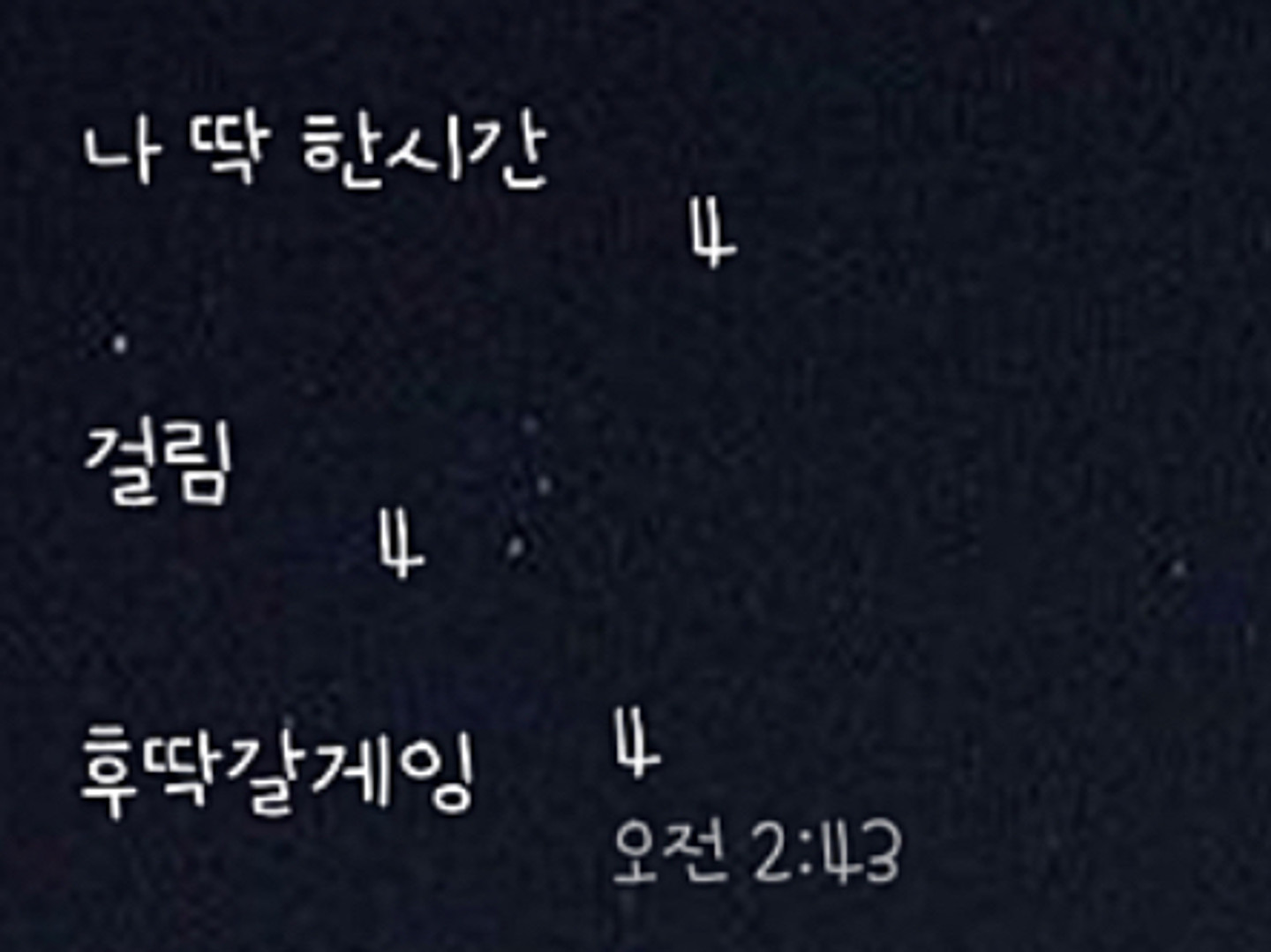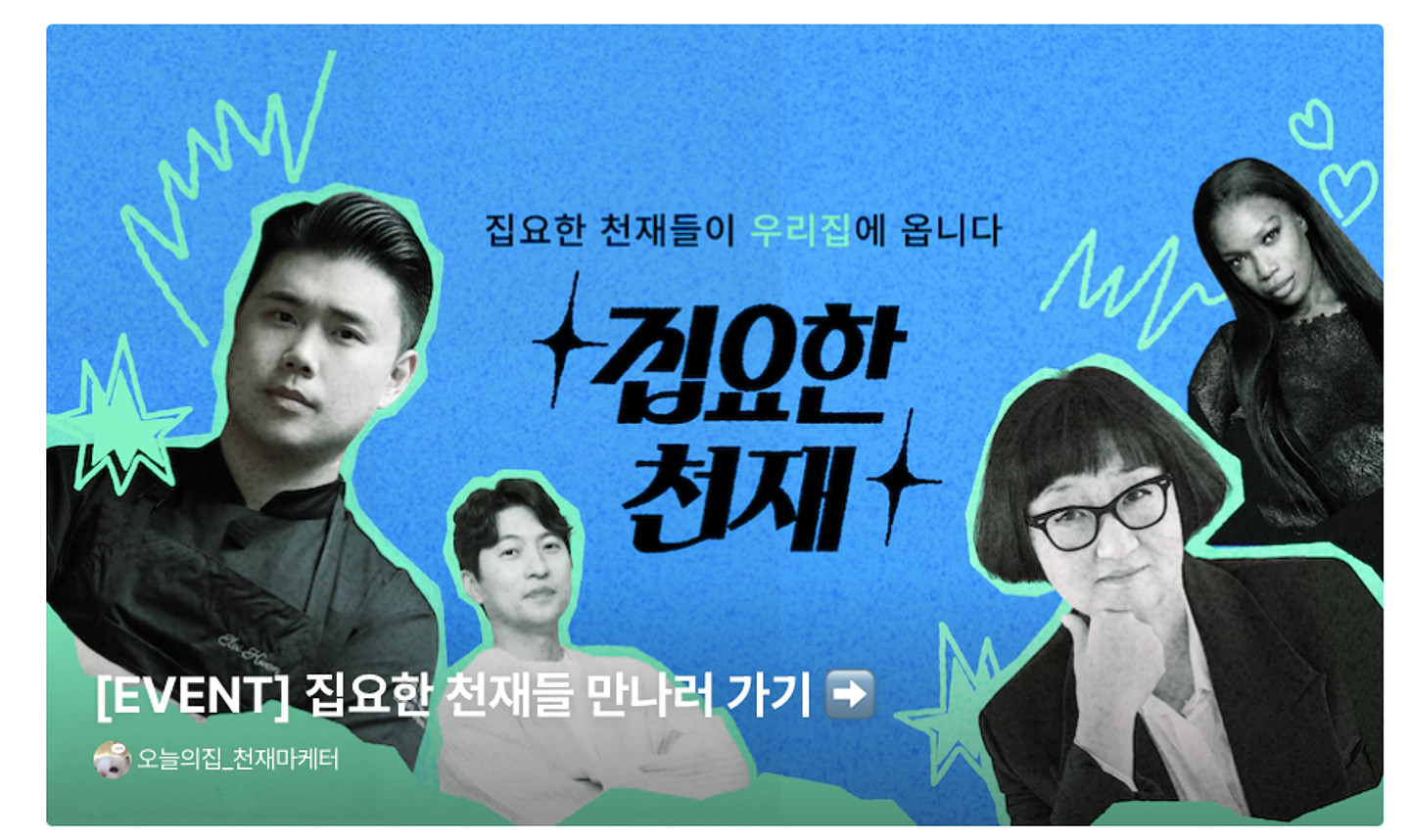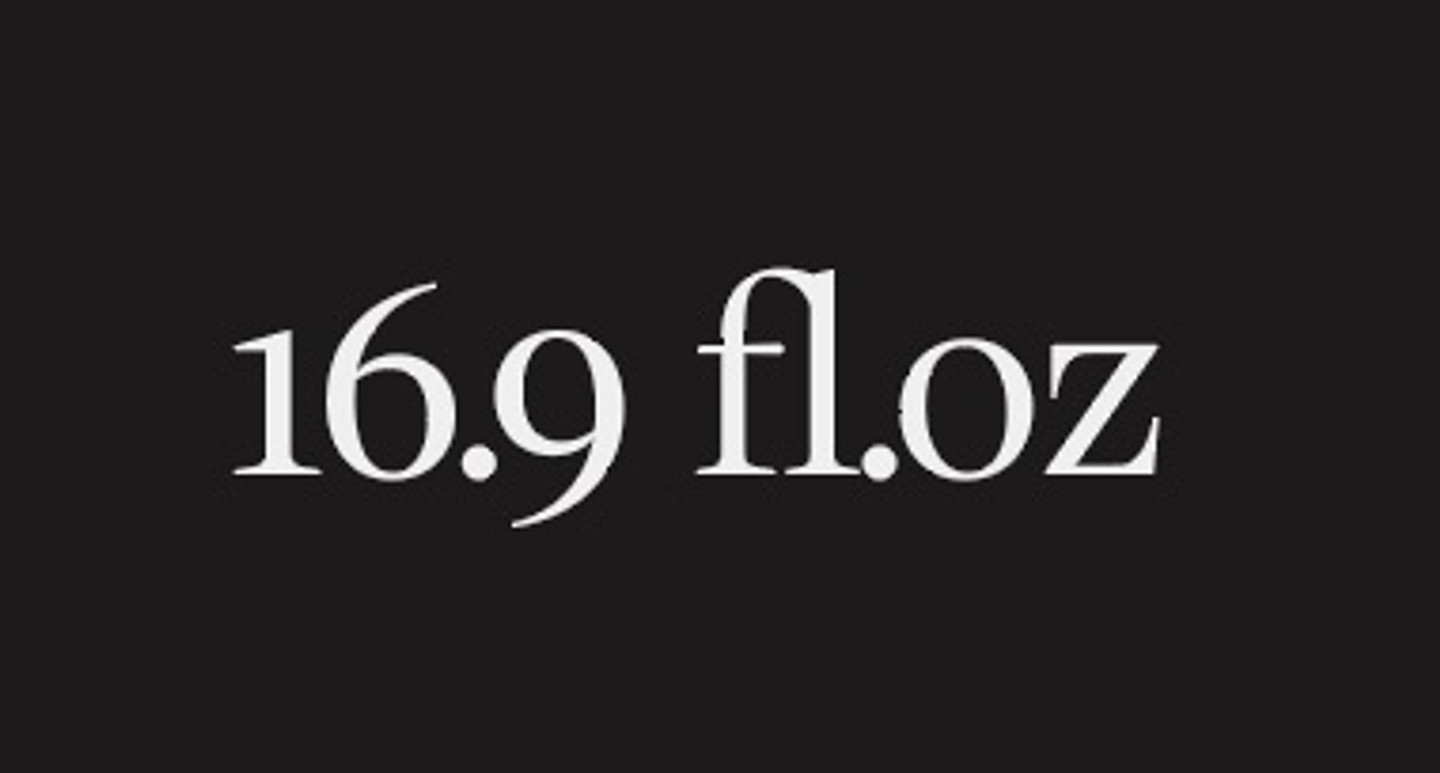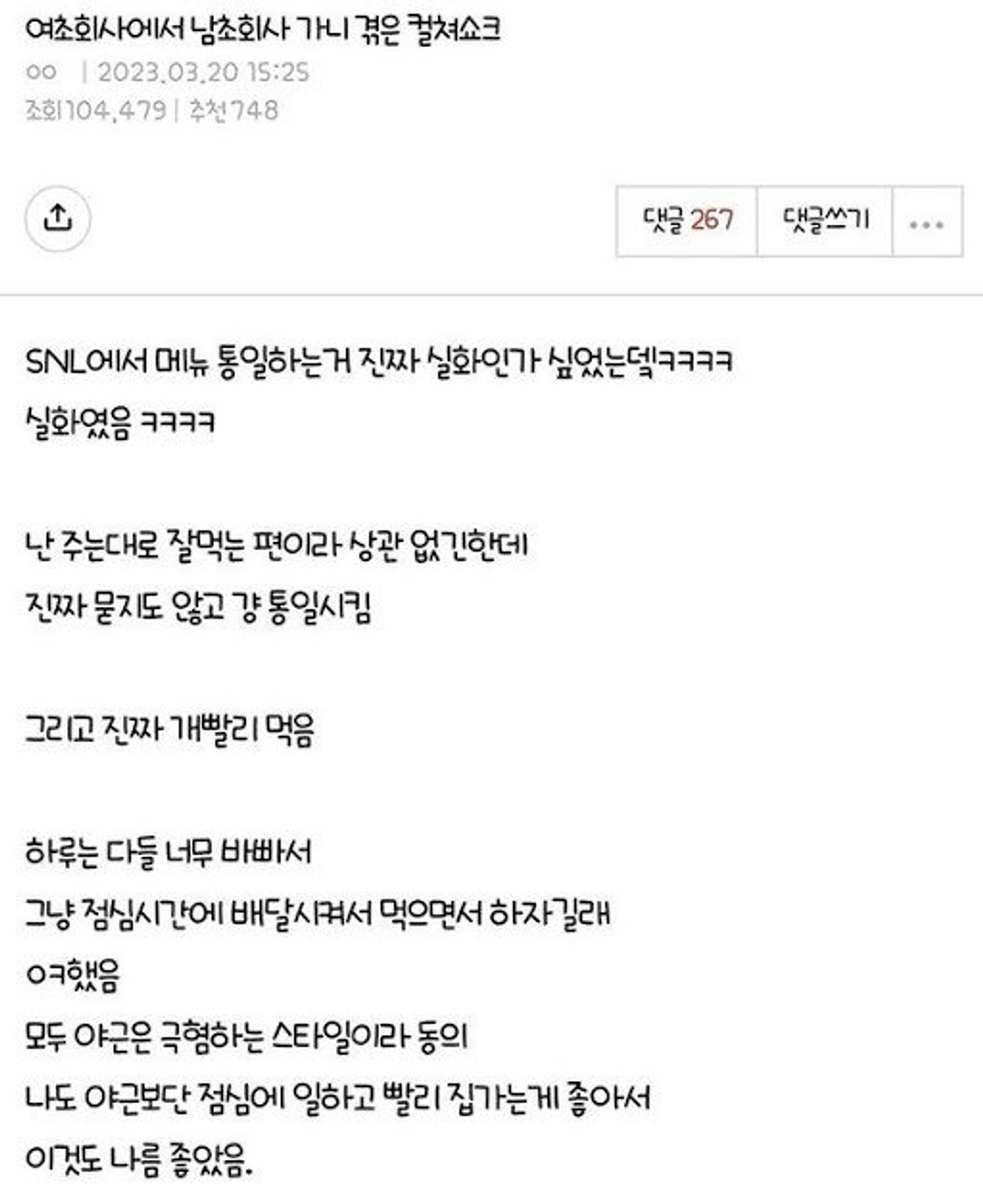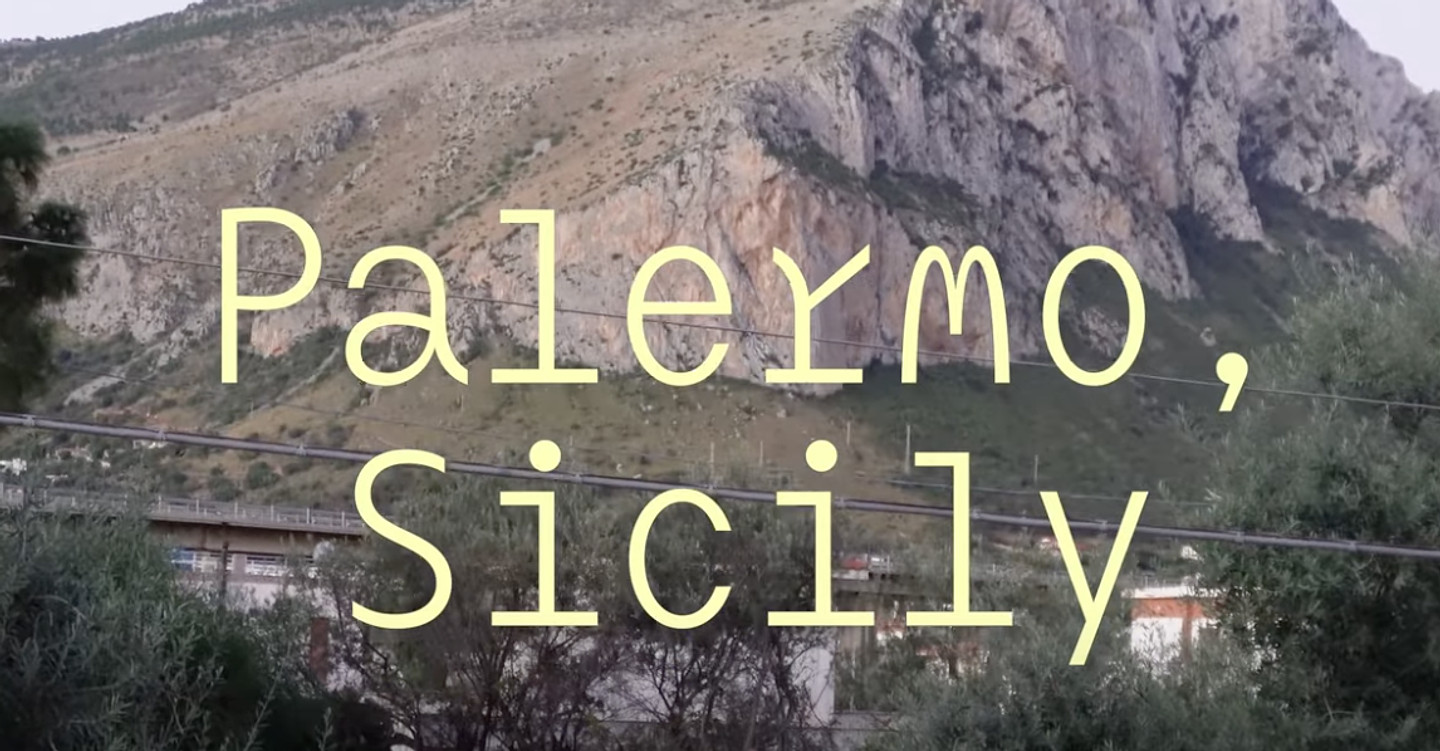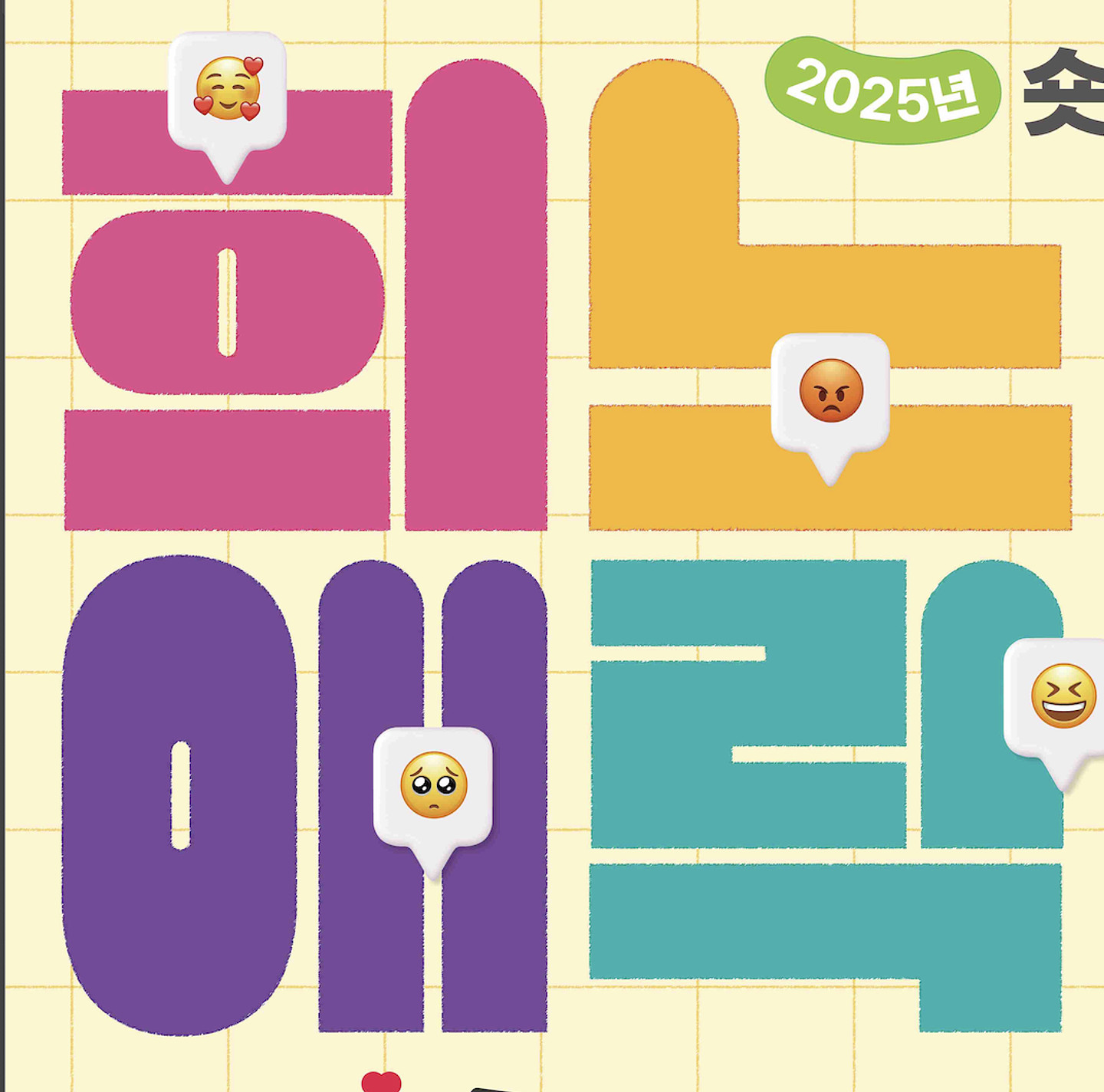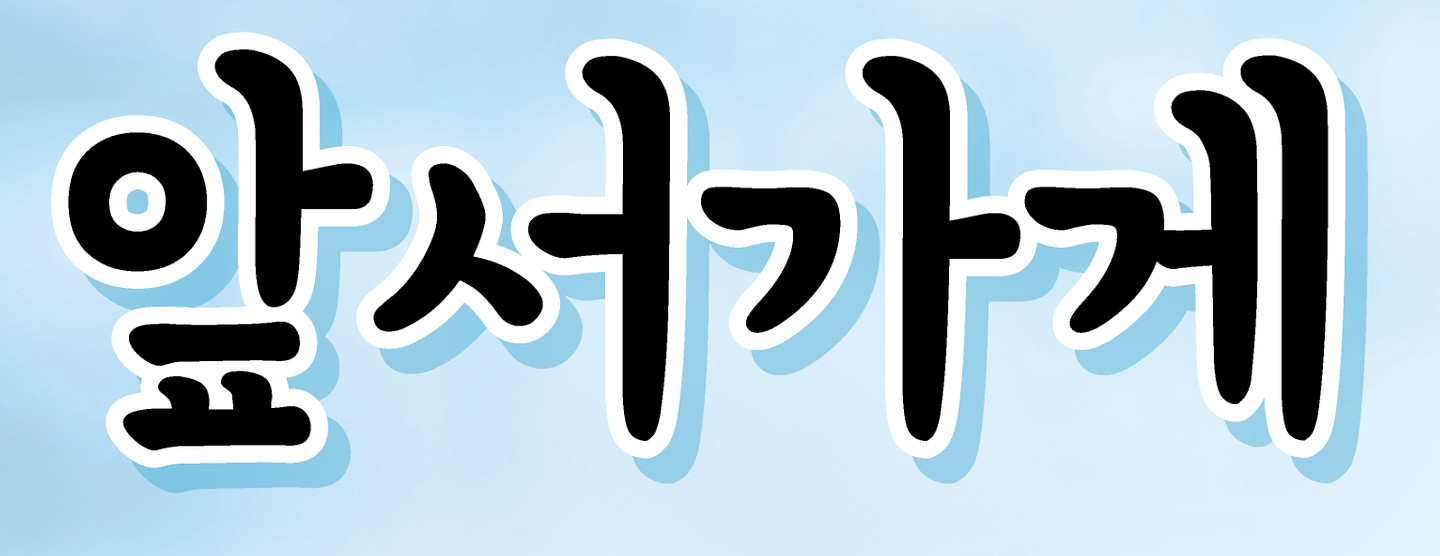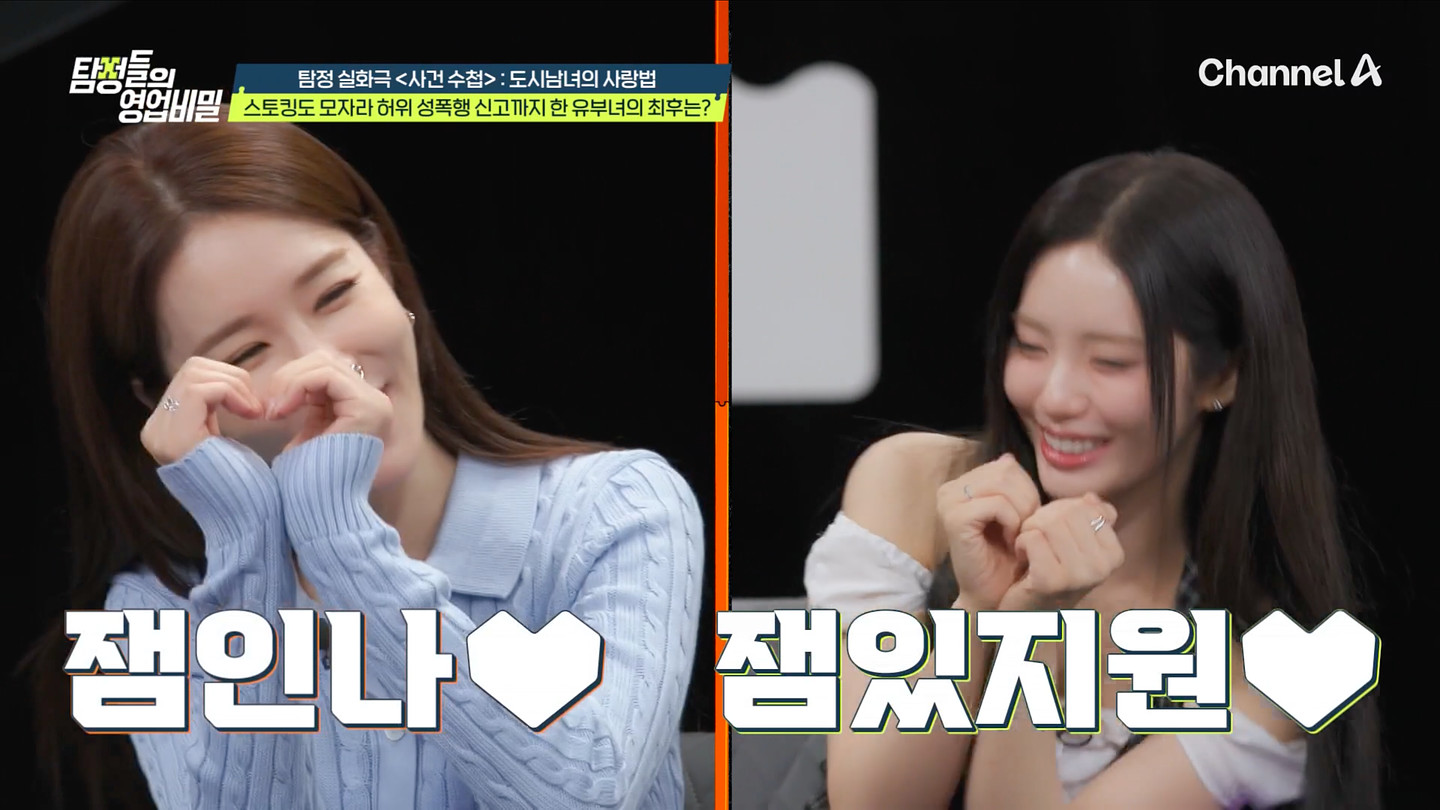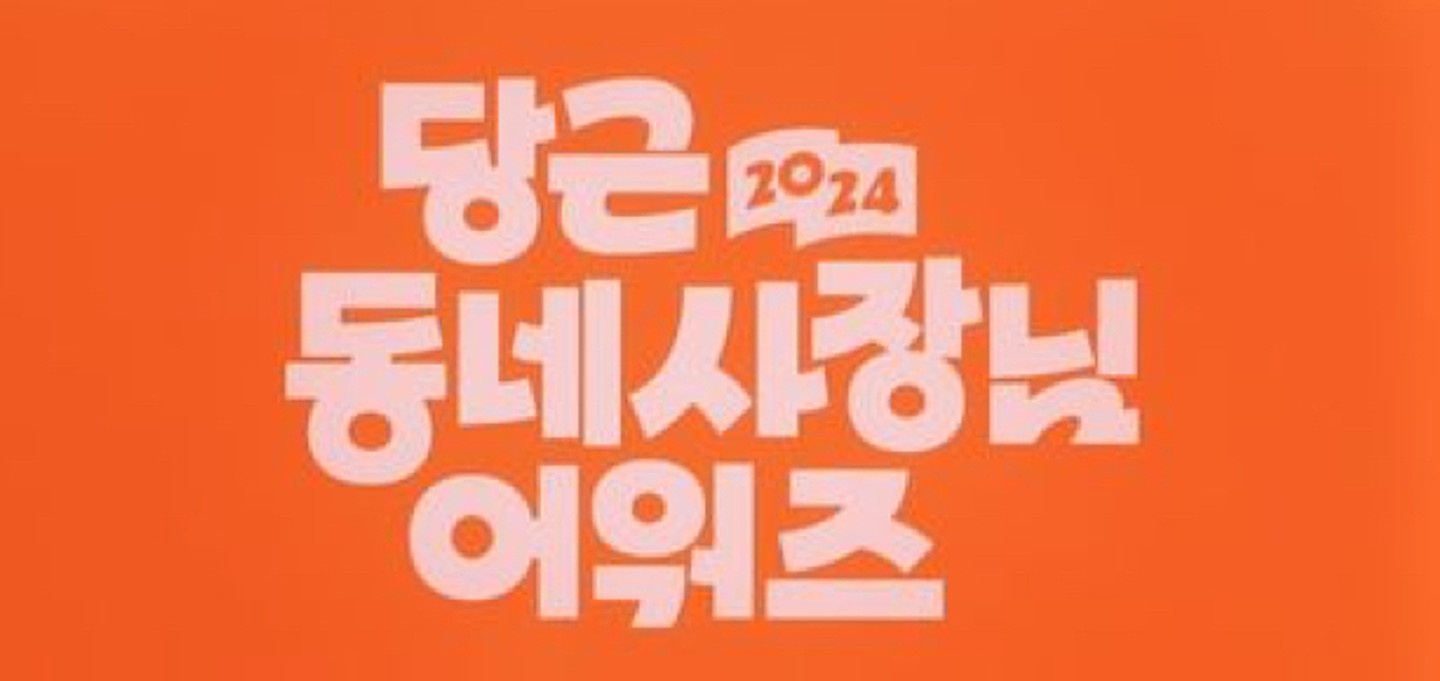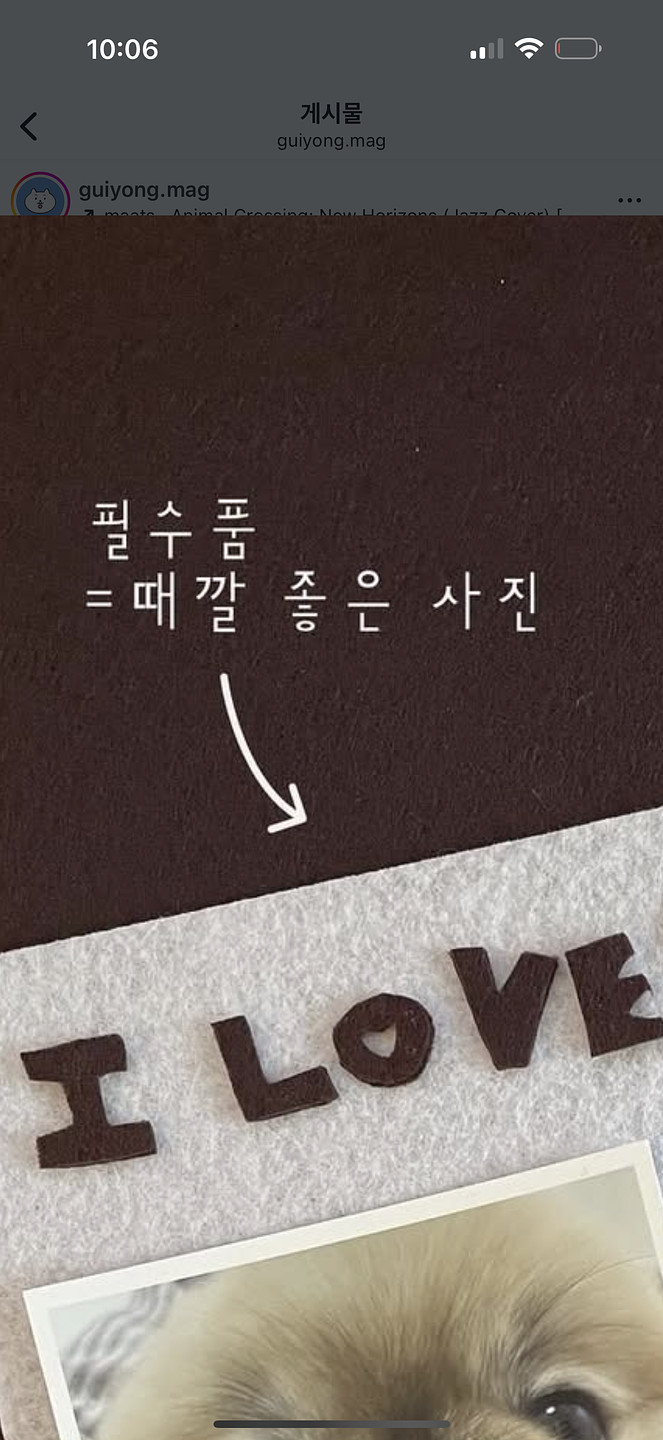
쇼츠에 많이 나오는 글씨체 같은데, 어떤 글씨체 일까요? ^^;
혹시 해당 폰트 어떤건지 알 수 있을까요 ??
이거 무슨 폰트일까요 ㅠㅠ 오늘까지 마감이라 급한데 도와주세요 ㅠㅠ
이 폰트 뭔지 알 수 있을까요ㅠ 리센느 원이 유튜브 거제 1편에 쓰인 폰트입니다
무슨폰트인가요?~ 알려주시면 진심으로 감사드리겠습니다. 감사합니다 ^^ 즐거운 주말되세요
이 폰트 아시는 분 있으신가요?ㅜㅜ 급해요 도와주세요
뭘까요 이폰트는?
이 영문폰트 뭘까요?
귀여운 폰트 궁금해요~!
이 글씨체알수있을까요
이글씨체알수잇을까요
아르헨티나 폰트 아는 폰트인데 이름이 기억안나네요
너무 흔해 보이는 폰트라서 정작 이게 어떤 폰트인지 구별하기가 힘드네요. 능력자분들 도와주세요 ㅠㅠ
이 폰트 뭘까요ㅠ
폰트 아시는 분 계실까요 ㅠ ㅠ
위아래 무슨 폰트일까요?
1,2 물결 모양이 다르네요 3,4 점 모양이 다르네요 무슨 폰트들 일까요?
손글씨같은데 어떤 글꼴인지 전혀 모르겠어요.. 아시는 분 계실까요?
핀터레스트에서 많이 보던 짤인데 폰트가 뭘까요?
이 폰트 뭔지 알 수 있을까요??
이 폰트 뭘까요..? 효과? 같은건 어떻게 한걸까요? 미리 너무 감사드립니다 좋은 하루 되세요~!
이 글쎄체 아시는 분 있을까요 ..
이폰트는 무슨 글씨체 인가요??
이 폰트는 무슨 글씨체 인가요??
이 폰트 뭘까요? ㅠㅠ
이 폰트는 뭔가요? 굴림체라기에는 굴림체가 상업적 용도로 쓸 수 없는 걸로 아는데 상업용이어서 궁금합니다!
오트밀 컬러 베이직 민소매 (라임색으로 된 글꼴 이름이 뭘까요 ...)
무슨 폰트인가요?ㅠ ㄹ이 z처럼 표현되는게 특징입니다
이 폰트 HU하늘고딕 140로 알려주셨는데 느낌은 비슷하지만 히읗이 다르고 사진 속 폰트가 획이 더 긴 느낌이라 정확히 알려주실분 ㅜㅜ
이 폰트 어떤건가요? 찾아봐도 안나오네요 ㅠ
무슨폰트일까요..?
무디교회 글씨체 무엇인지 아시나요?ㅠㅠㅠㅠ못찾겠어요 도와주세요!
무슨 명조체일까요...?
무슨 폰트일까욥?
이 폰트 무엇인지 아시는분 계실까요?
혹시 해당 폰트는 어떤 폰트인지 알 수 있을까요 ??
폰트 궁금해요..!!
고수님들 용동초에 쓰인 글꼴좀 알려주세요
무슨폰트인지 찾아 주세요
혹시 해당 폰트는 어떤 폰트일까요 ??